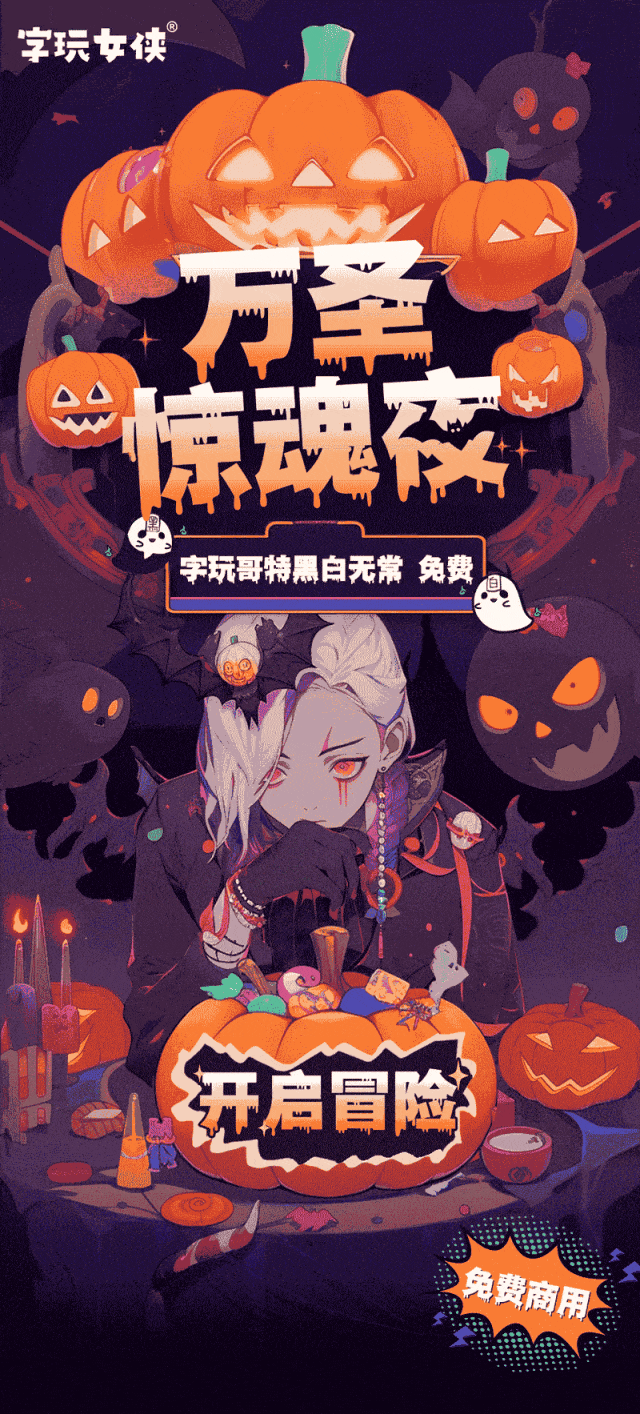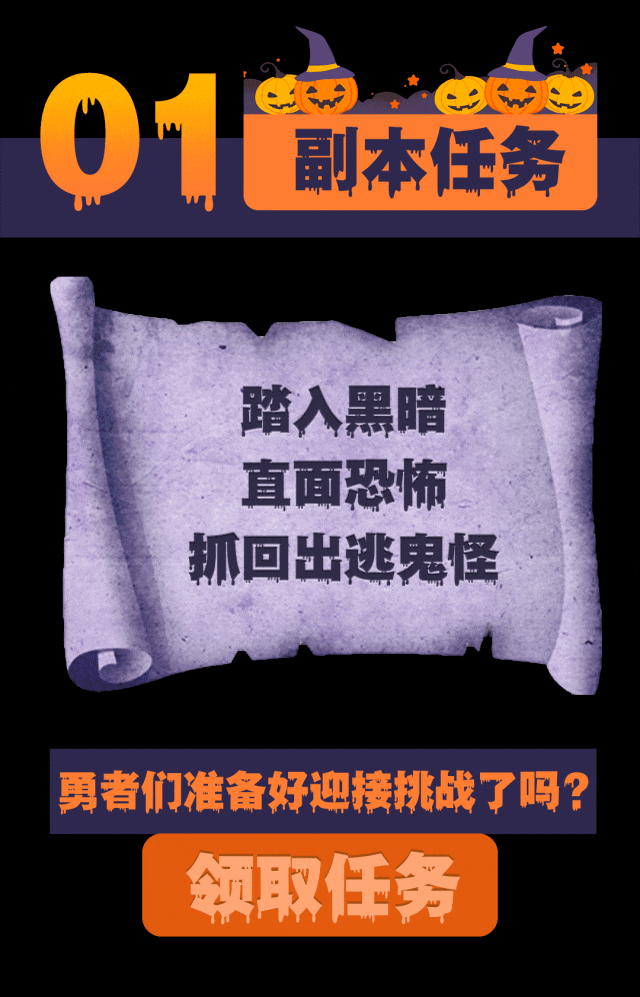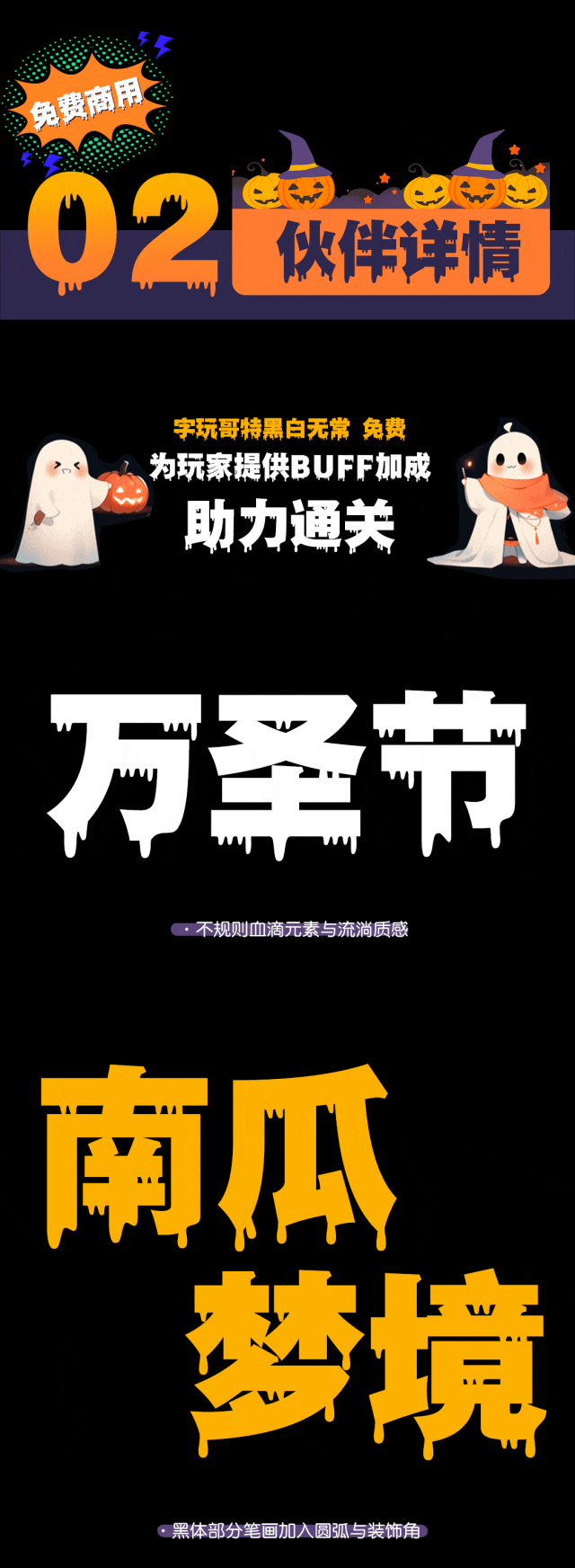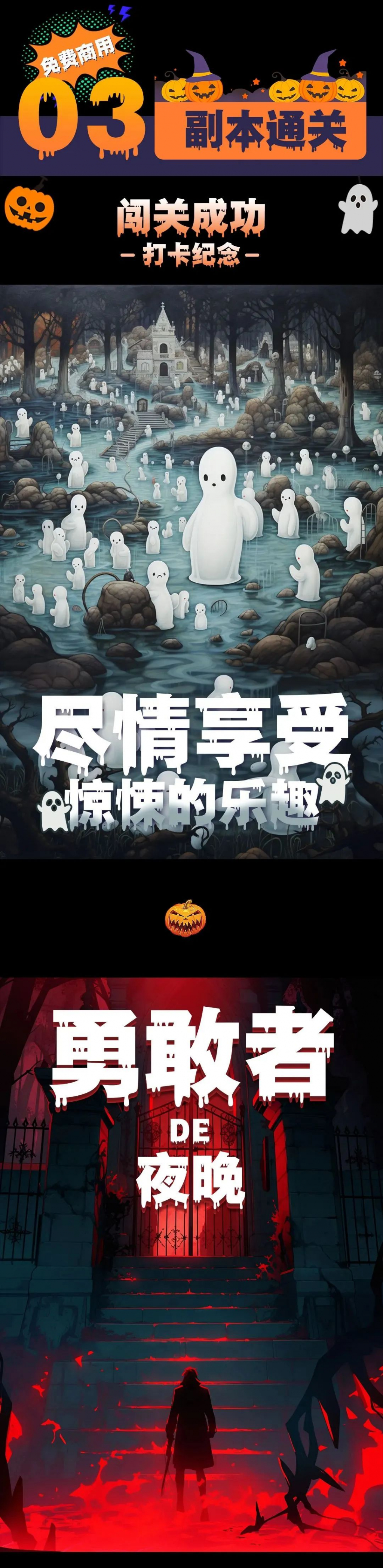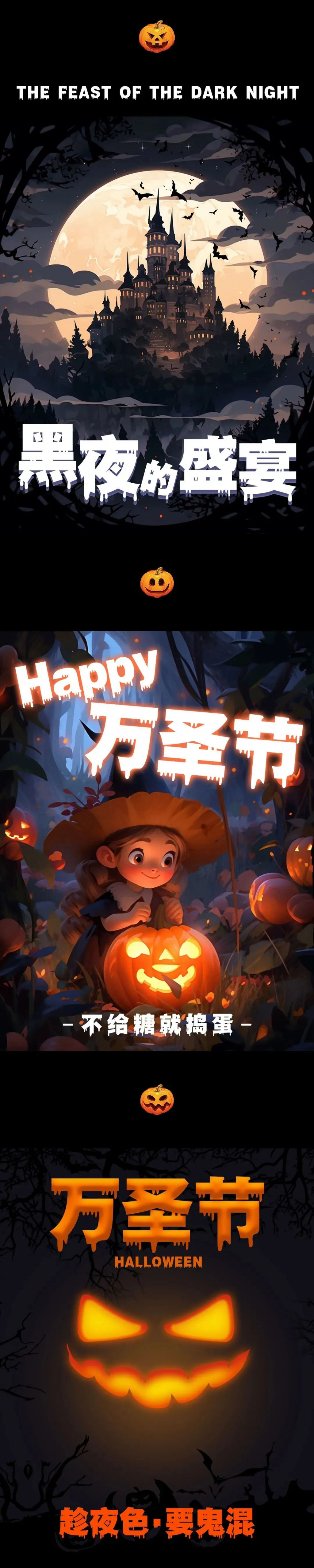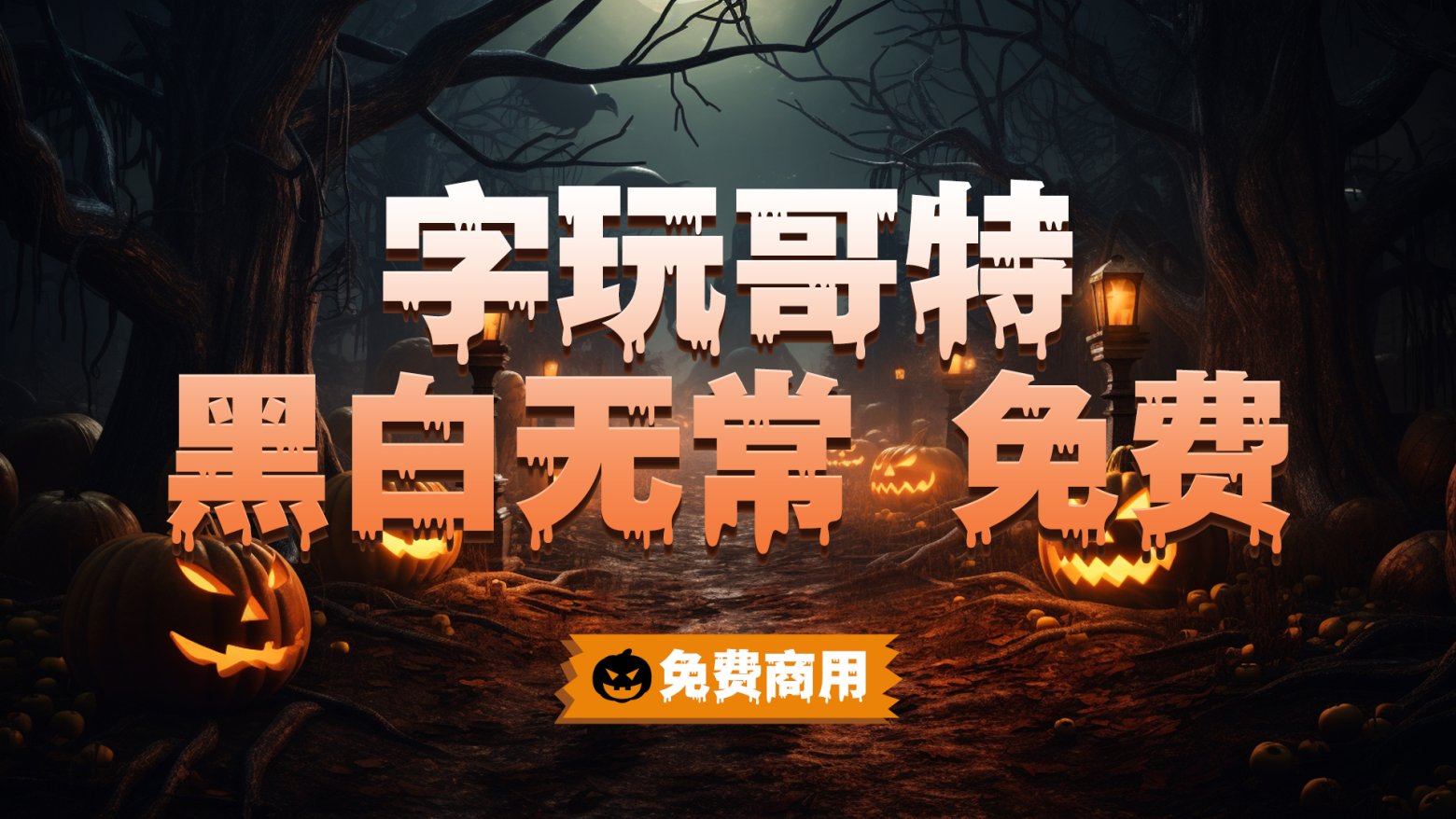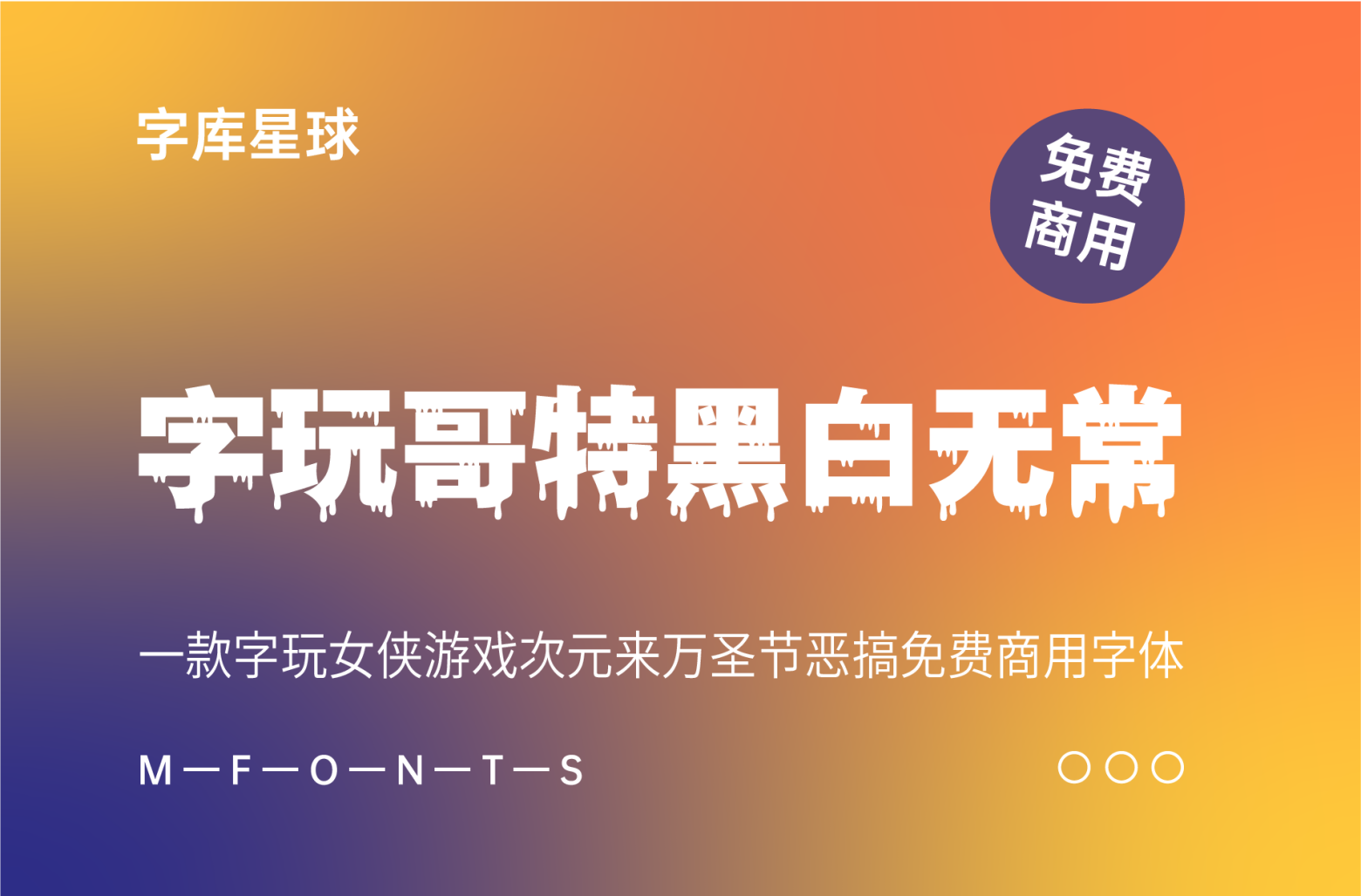
当夜幕降临,万圣节的魔法笼罩大地
烈焰舞动,鬼魅嬉戏,百鬼夜行
字玩女侠化身字玩哥特黑白无常
带领我们前往游戏异次元
挑战充满冒险与刺激的万圣节游戏副本~
字玩哥特黑白无常 免费」是字玩女侠游戏次元字体字库推出的首款万圣节主题免费商用字体,支持全场景(除软件内嵌与LOGO)免费商用。字体汇取了阴森、诡异、恐怖之感,并将鲜血这一哥特风格代表元素融入字型,营造万圣节恐怖氛围和紧张感。
「字玩哥特黑白无常 免费」作为万圣节主题字体,加入了不规则血滴元素与流淌质感,黑体部分笔画加入圆弧与装饰角,通过血腥的效果与令人感到不安和恐惧的装饰元素,为字体增添视觉冲击以及惊悚感。